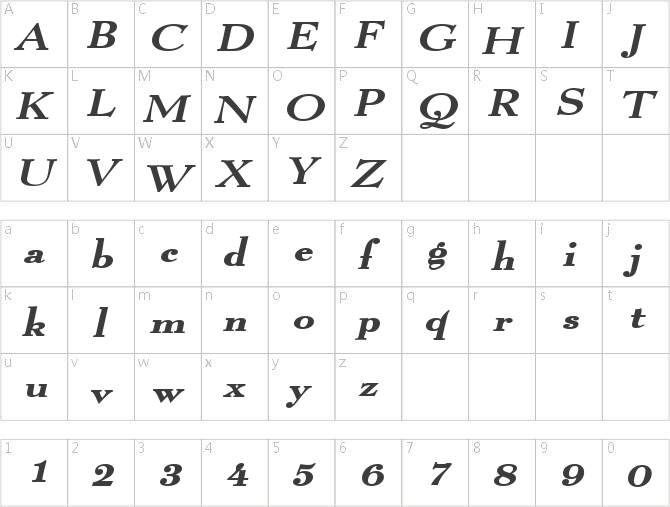
字体名称: Luciano
Luciano-Wide-BoldItalic
Luciano-Wide-BoldItalic介绍
Luciano-Wide-BoldItalic字体字库是一款让人赏心悦目、百看不厌的英文字体,适合各类广告和产品包装设计应用,字体大小0.07MB,格式为ttf字体,上传用户是高塔。,作者/版权方为未知